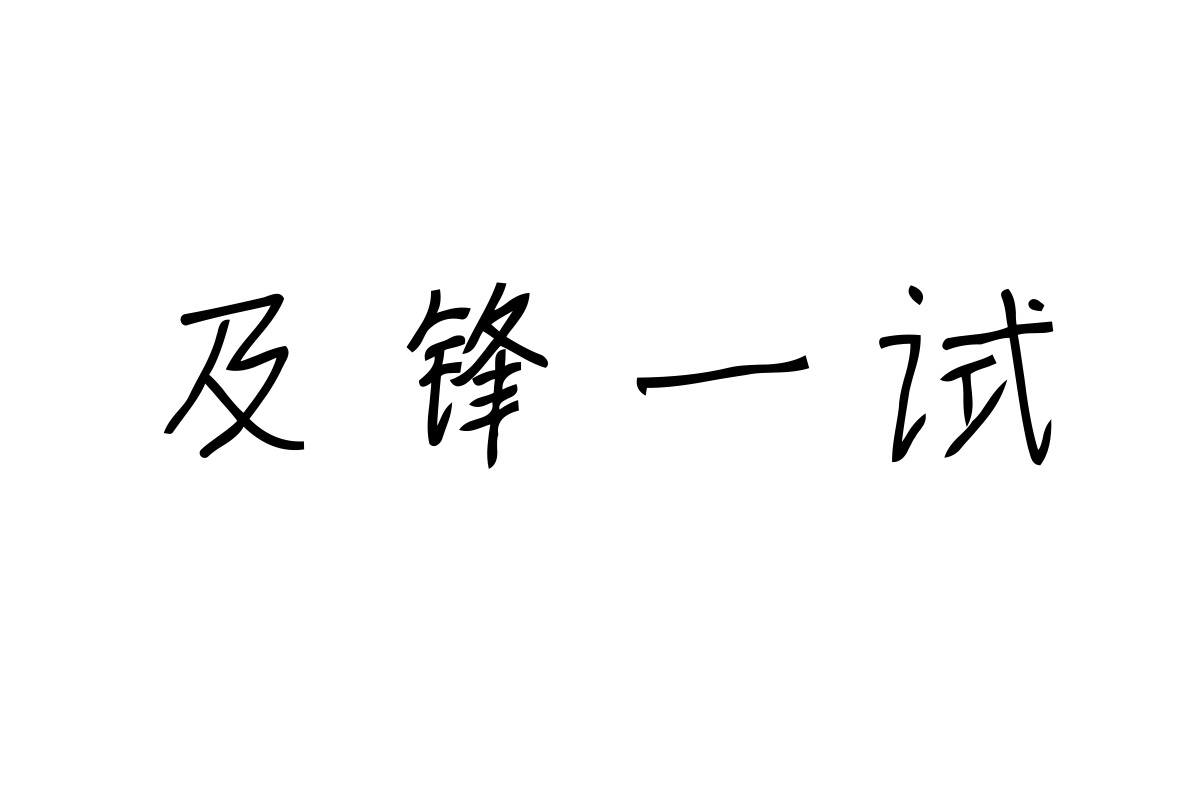
蝉羽小时候的字是一种具有独特韵味和风格的字体。它采用了传统的书法艺术,结合了现代设计元素,使得字体既有古典之美,又不失现代感。这种字体适合用于需要展示传统文化、艺术或诗词的场合,如书籍、杂志、海报等。
蝉羽小时候的字的特点包括:
1. 字形优美:字体线条流畅,结构严谨,给人一种优美的视觉享受。
2. 风格独特:字体融合了传统书法的笔触和现代设计的简洁,形成了独特的风格。
3. 易于识别:字体大小适中,笔画粗细均匀,容易让人一眼就能认出。
4. 适用范围广泛:适用于各种场合,如广告、宣传、包装设计等。
总之,蝉羽小时候的字是一种具有独特韵味和风格的字体,适合用于需要展示传统文化、艺术或诗词的场合。